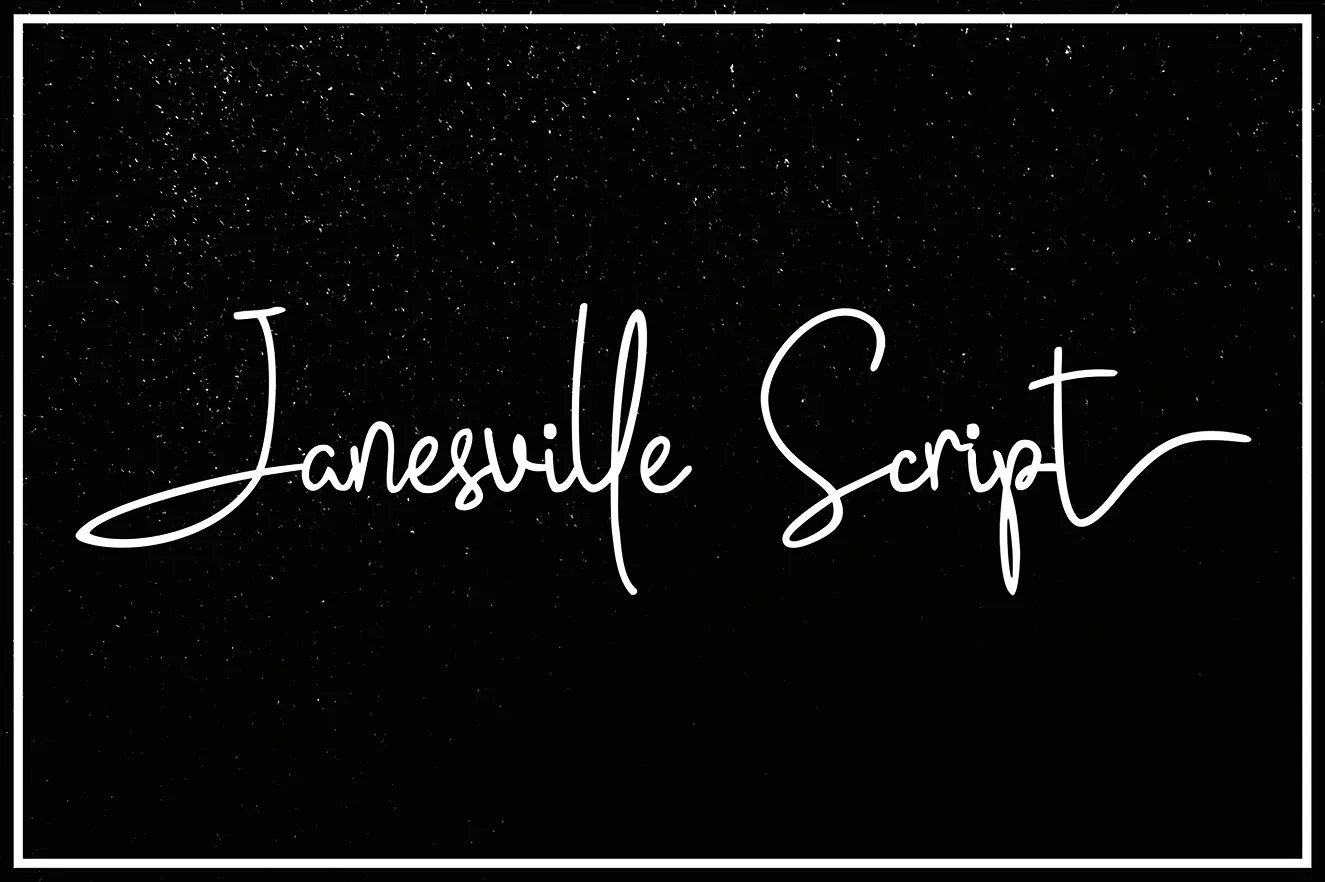
Descubra agora a Janesville Script Font, uma fonte script premium criada pelo Fargun Studio. Introduzida para oferecer uma escolha incrível no seu design e personalização de logotipos ou materiais publicitários, essa fonte é perfeita tanto para um t-shirt customizada quanto para o seu próximo projeto de web site ou impressão digital. Com sua elegância fluida e detalhes suaves, a Janesville Script permite criar mensagens poderosas que se destacam. Seja em aplicações como assinaturas, identidade visual, cartões de convidados de casamento, materiais para festas temáticas ou até mesmo nas etiquetas dos seus produtos, esse é um recurso gráfico de alto nível e com uma oferta incrivelmente conveniente: gratuita hoje. Engane-se se pensa que a qualidade premium vem sempre junto com um preço elevado. A Janesville Script é uma oportunidade perfeita para incorporar elegância em seu próximo projeto sem sacrificar o custo.